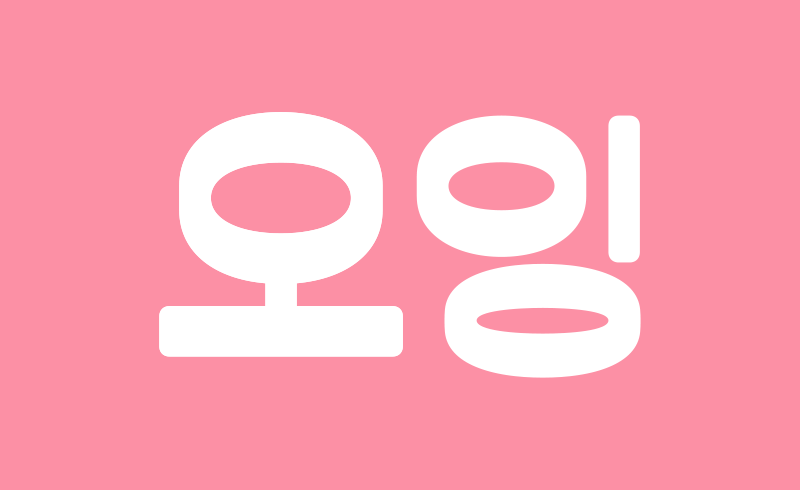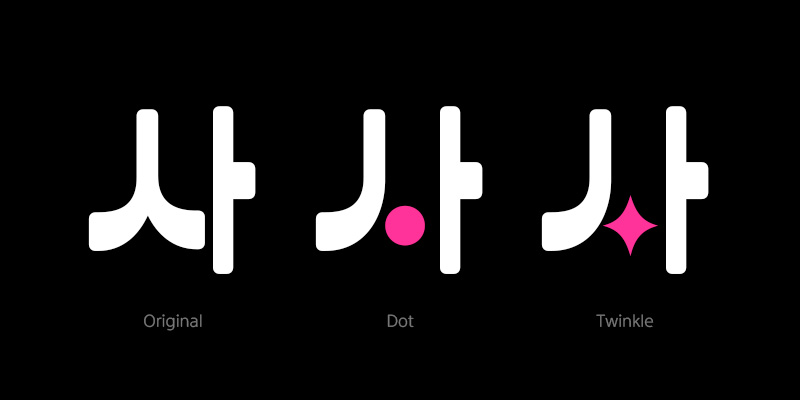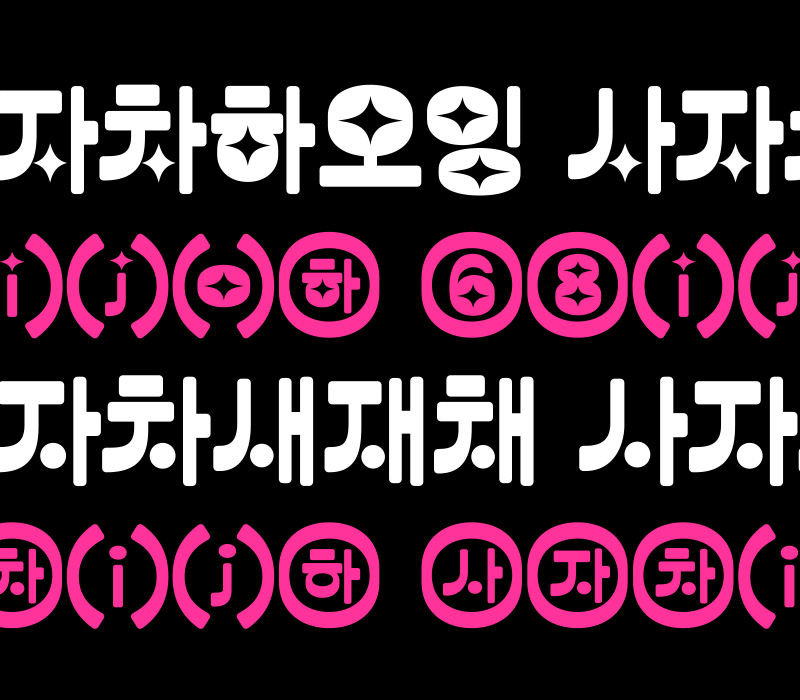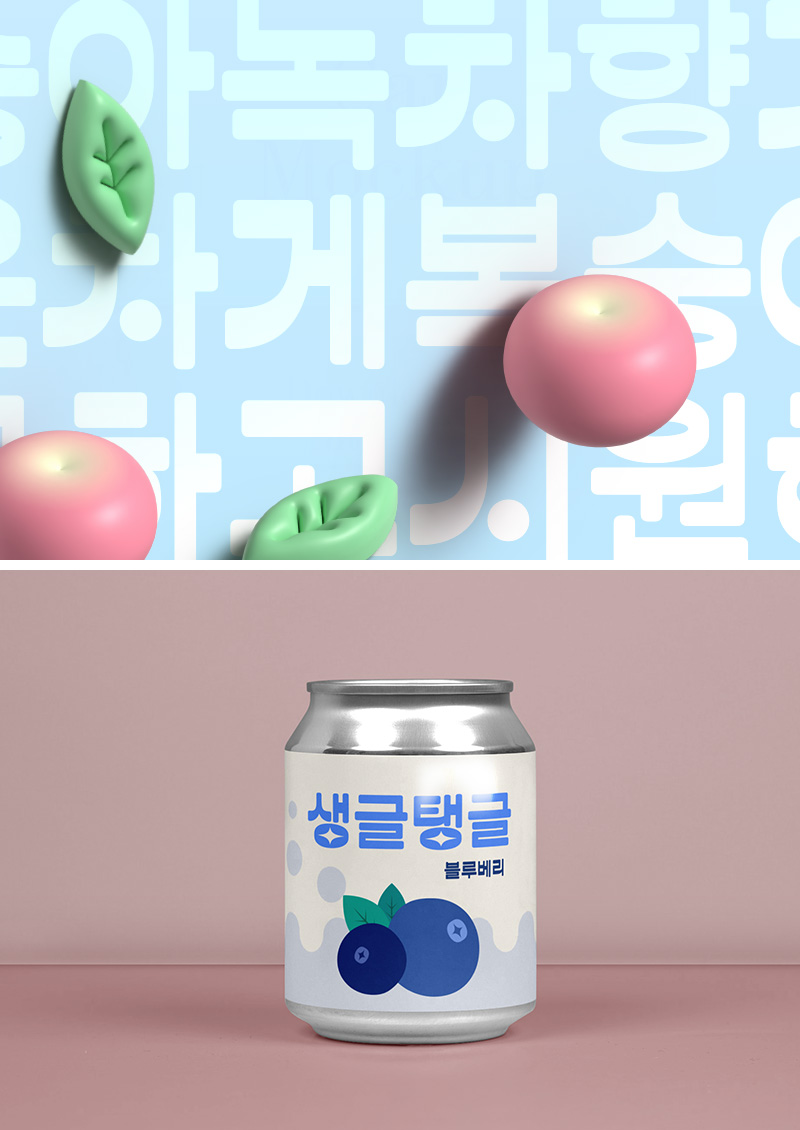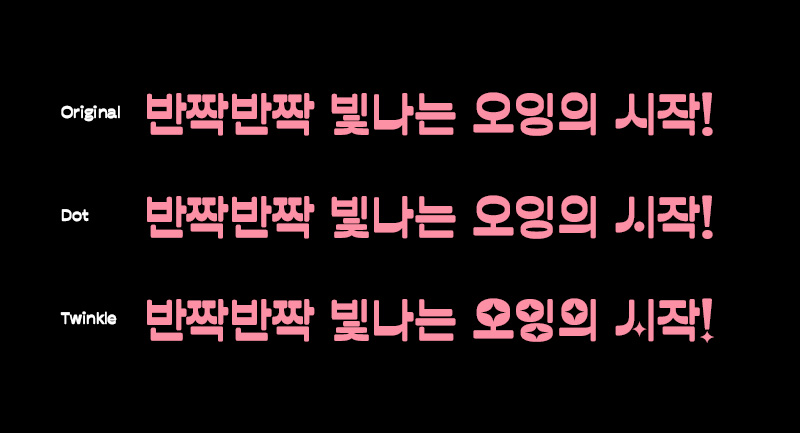
RixOing
3 Style - Original, Dot, Twinkle
Rix오잉은 'ㅇ'꼴의 유니크한 직선 포인트와 획 대비가 인상적인 글꼴입니다.
전체적인 획의 라운드 효과가 부드럽고 귀여운 인상을 줍니다.
각각의 특징이 돋보이는 세 가지 디자인으로 다양하게 활용하기 좋습니다.
FontFamily Rix오잉 / RixOing
Design Lee Su-ha
Direction Park Yong-rak
Glyphs 2,350 + 430 KR Characters / 94 Latin Characters / 986 Symbols
Rix오잉은 Original, Dot, Twinkle 디자인 3종을 지원합니다.
라운드 효과로 부드러운 인상을, 직선 구간이 있는 원형 형태로 유니크한 느낌을 주었습니다.
총 세 가지 디자인으로 다양성을 갖춘 서체입니다.
영문, 약물의 디자인은 한글과 동일한 특징을 가지고 있어 혼용 시 조화롭습니다.